书法是世界上少数几种文字所有的艺术形式之一。是中国汉字独有的一种传统艺术。中国书法的美是线的美、力的美、光的美和个性的美。博大精深的中国书法可以说是中华文化的基础缩影。而新时代书法更是经历了文字的创造、使用、演变、发展,见证了中华五千年文明的辉煌灿烂。接下来看看下面图片字体 ,来体会书法之美吧。
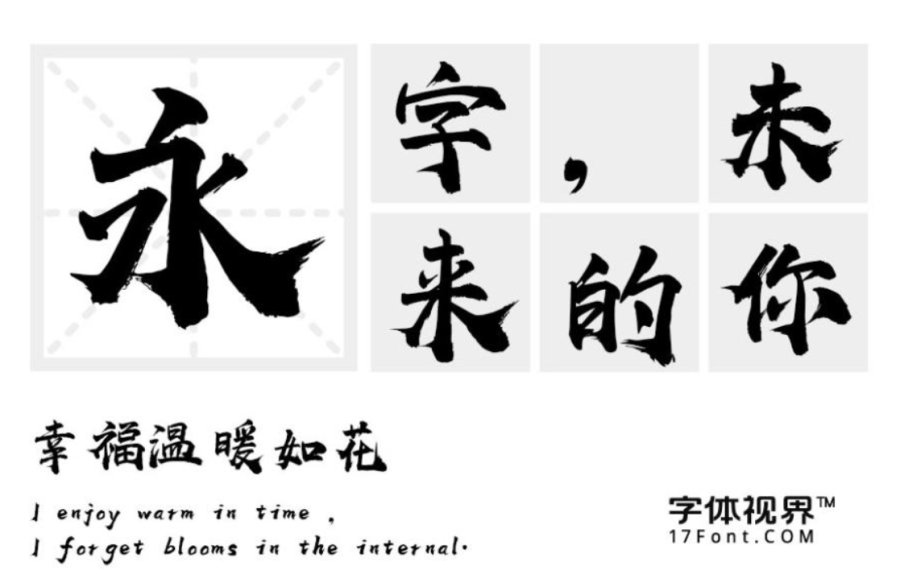
上首华凤书法:这款字体风格稳重呈方块形,字体笔画竖折处细节处理,是此套字库的亮点。字库整体特征坚硬、有力,具有现代、国际化的指向性,适用于搭配标志、广告标语、商业广告等高端属性。
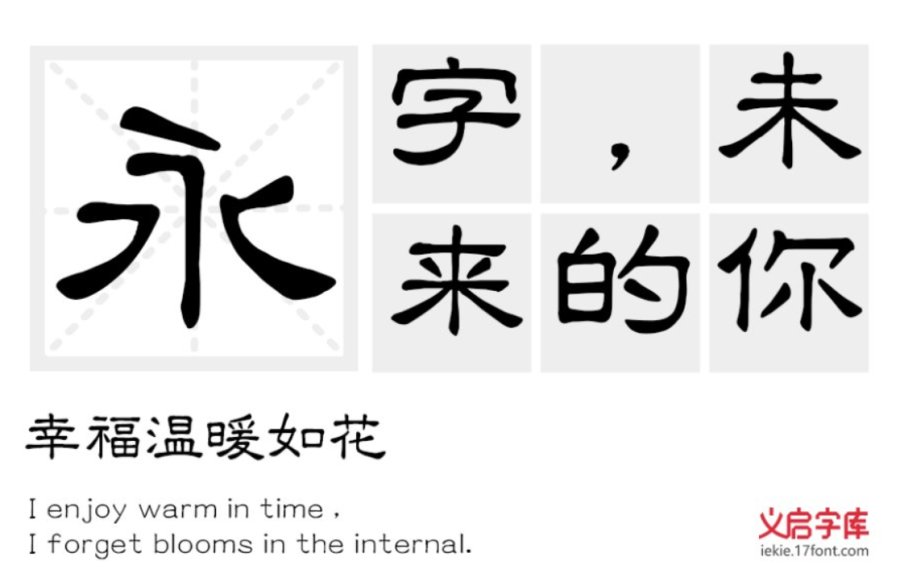
义启隶书体:隶书,是书法中常见的一种庄重的字体,书写效果略微宽扁,横画长而直画短,呈长方形状,而这款字体笔画上保留深化了波折的元素,考虑到整体的可塑性,起收处弱化方笔加强圆笔画,所谓蚕头雁尾修饰弱化些章法,左右波折遥相呼应,气息通畅一气呵成。适用于标题、正文、印刷、屏显等领域。
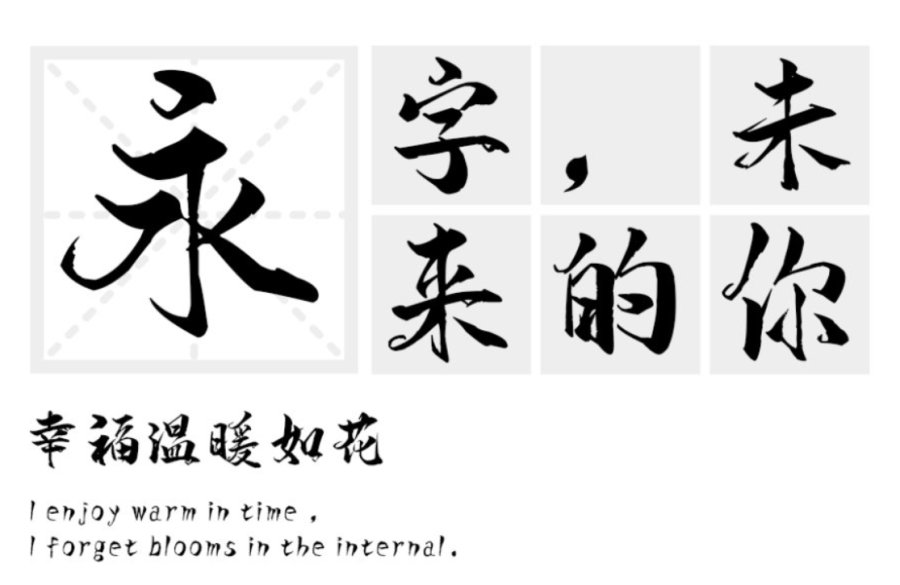
汉标智造国楷:这款字体书法气息浓厚,结字潇洒俊逸,运笔行云流水,气韵生动。适用于文艺类的书刊、品牌广告和产品包装设计,以及社交网络的个性化用字。